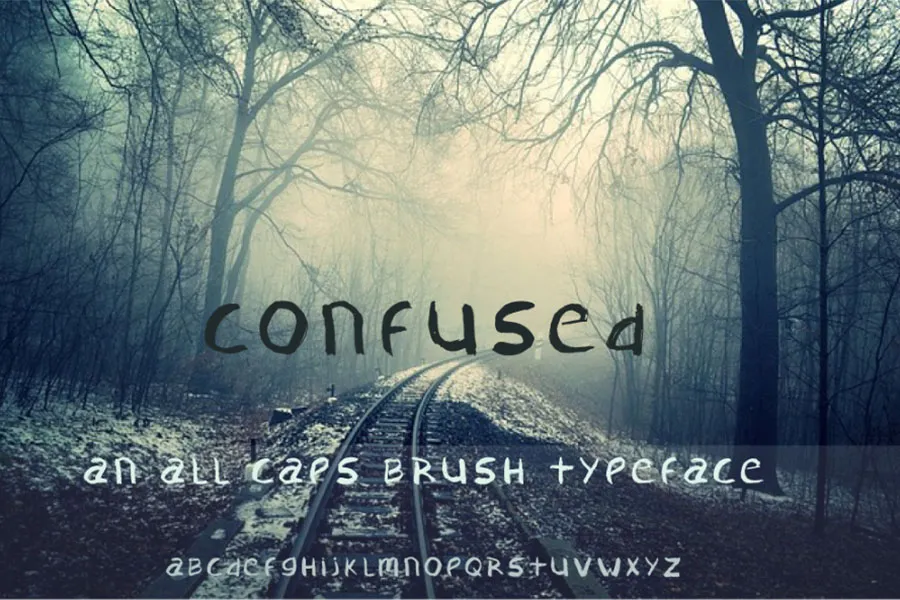
A confusa tipo ‘Confused Typeface’, criada pelo designer Hamilton, é uma opção única para quem busca adicionar um toque especial a mensagens digitais e publicações online. Com traços suaves e delicados que remetem ao estilo da caligrafia à mão, esta fonte oferece uma textura natural e envolvente sem perder o poder de legibilidade essencial. Perfeita para gráficos personalizados ou design editorial, a ‘Confused Typeface’ pode ser usada em tudo desde cartas de email até publicações online e materiais de marketing. Seu estilo delicado faz dela uma escolha ideal para criar um visual único e autêntico que conecta-se aos seus seguidores. Com seu designer cuidadosamente detalhado, a ‘Confused Typeface’ é uma fonte brash perfeita para quem busca criar um design gráfico mais artístico e personalizado, sem deixar de lado a importância da legibilidade.